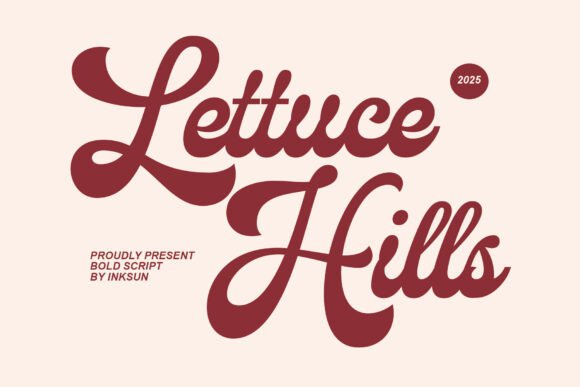
Lettuce Hills
Trouver les bons éléments de conception peut être un défi, mais Lettuce Hills propose une collection exceptionnelle qui rehausse instantanément votre travail.
Que vous créiez des produits POD (impression à la demande), des invitations de mariage ou des visuels pour les réseaux sociaux, Lettuce Hills est un choix idéal.